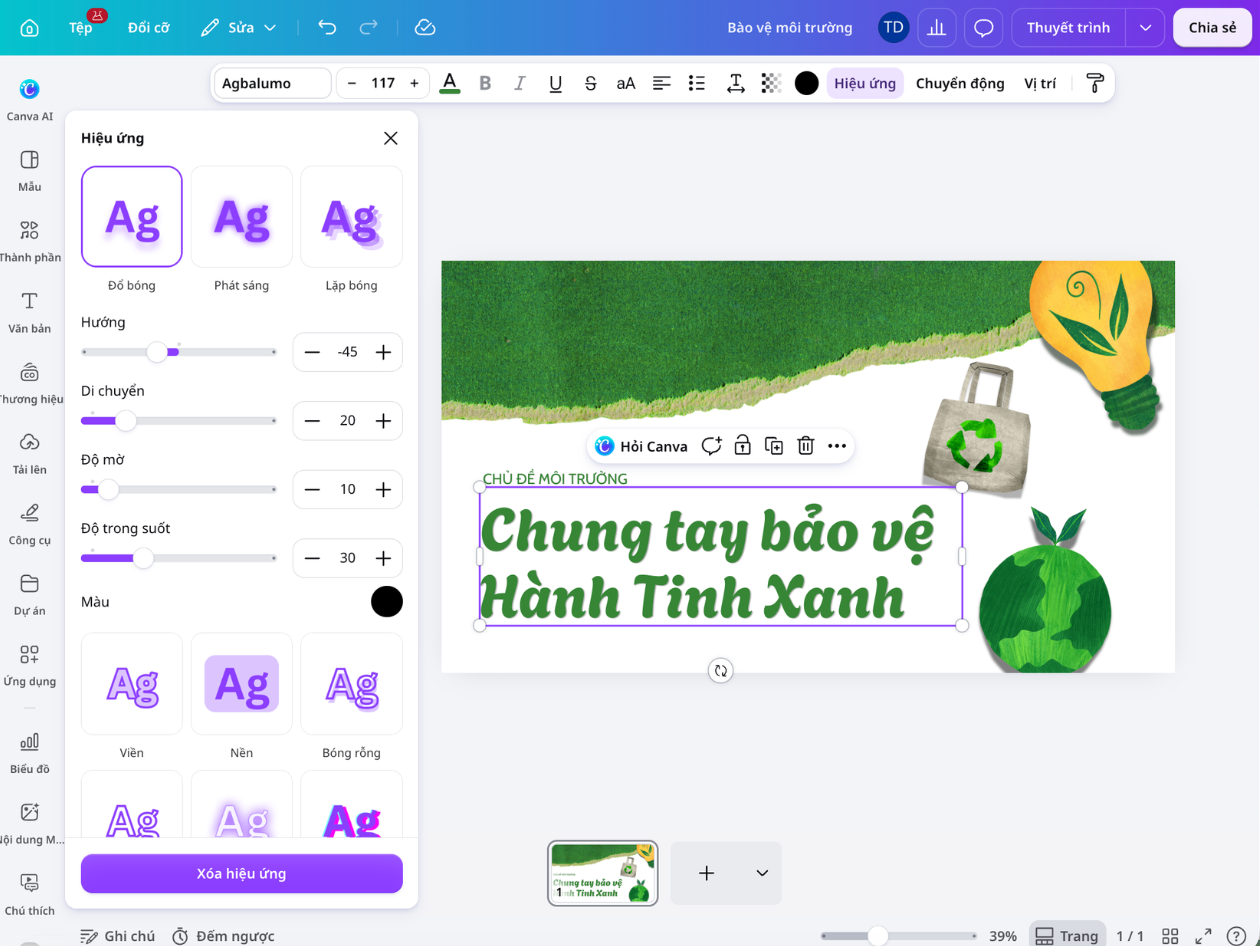
Mỗi font chữ viết tay mang một sắc thái riêng để câu chữ phù hợp hơn với cảm xúc của thiết kế. Baystar Script thanh thoát cho thiệp mời, tên riêng và câu trích dẫn, trong khi Nordminne Script tạo nét cọ đậm và giàu biểu cảm.
CoalhandLuke đem lại vẻ thô mộc, gần gũi. Anaconda Wildstyle và Owltail Brush tạo chuyển động mạnh cho tiêu đề, còn Handpicked Seashells hay Spilled Ink phù hợp với những ý tưởng vui tươi, sáng tạo và ít trang trọng hơn.
Thư viện đa dạng giúp bạn bắt đầu từ tinh thần muốn truyền tải thay vì đoán theo tên font. Từ lời chúc dịu dàng đến poster cá tính, mỗi thông điệp đều có kiểu chữ phù hợp với vai trò trong bố cục. Nét đẹp riêng vẫn hiện rõ mà không làm người đọc mất tập trung.
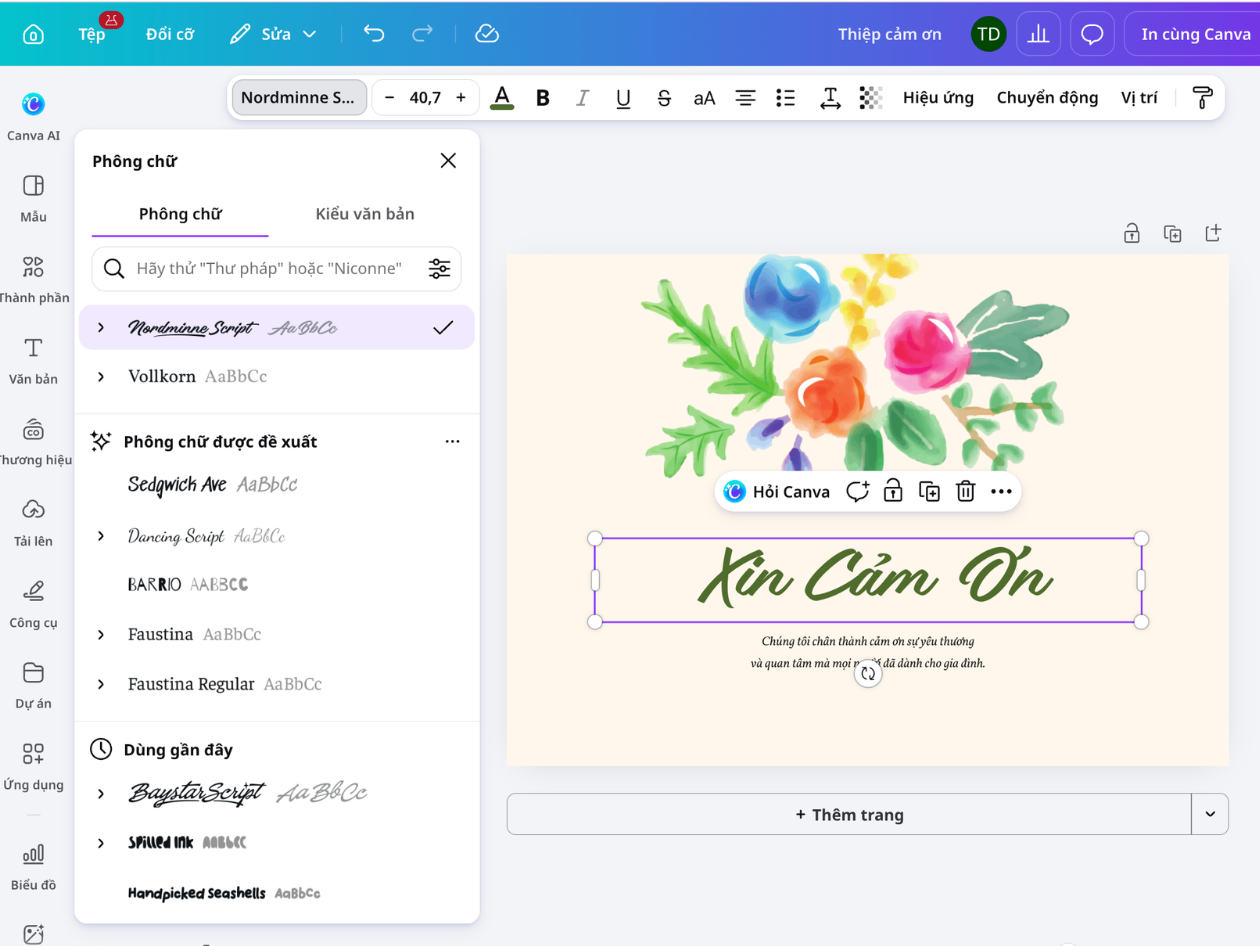
Font viết tay tiếng Việt cần thể hiện trọn dấu để cảm xúc không bị gián đoạn bởi những ký tự khó đọc. Các lựa chọn hỗ trợ tiếng Việt giúp tên riêng, lời chúc và tiêu đề giữ được hình dáng cân đối ngay cả khi nội dung có nhiều dấu.
Khả năng hiển thị được cảm nhận rõ nhất trên chính câu chữ sẽ xuất hiện trong thiết kế. Những ký tự như ă, â, ê, ô, ơ và ư cho thấy dấu có chạm nhau, quá nhỏ hoặc làm nhịp chữ trở nên nặng nề hay không.
Khi phần chữ rõ ràng, nét viết tay mới phát huy được sự mềm mại và gần gũi vốn có. Bạn dễ chọn kiểu chữ vừa truyền đúng cảm xúc, vừa bảo đảm người xem nắm bắt thông điệp mà không phải đọc lại.
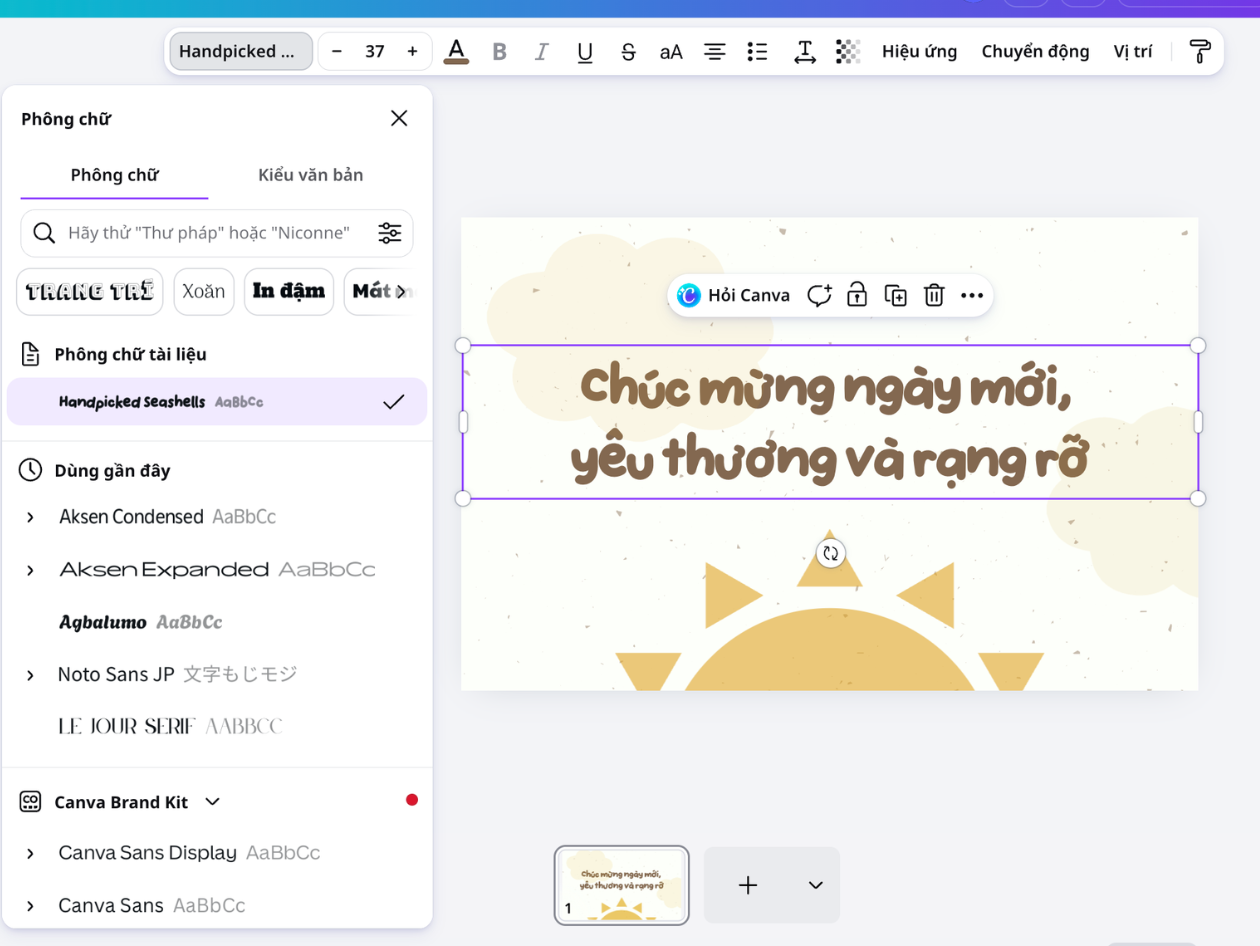
Một font đẹp trong bảng mẫu có thể tạo cảm giác hoàn toàn khác khi đặt cạnh ảnh, màu nền và khoảng trống. Canva cho phép xem kiểu chữ ngay trên hộp văn bản đang dùng, để từng lựa chọn được đánh giá trong đúng bố cục.
Chiều rộng tiêu đề, cách xuống dòng và độ tương phản trở nên rõ ràng khi câu chữ xuất hiện ở kích thước thật. Nhiều phương án có thể được so sánh để tìm ra kiểu vừa có chất viết tay, vừa giữ được trọng tâm thị giác.
Khả năng thử trực tiếp giúp quyết định về font gắn với toàn bộ thiết kế thay vì chỉ dựa vào sở thích riêng. Phần chữ vì thế hòa với hình ảnh tốt hơn và dẫn mắt tự nhiên hơn đến thông điệp quan trọng.
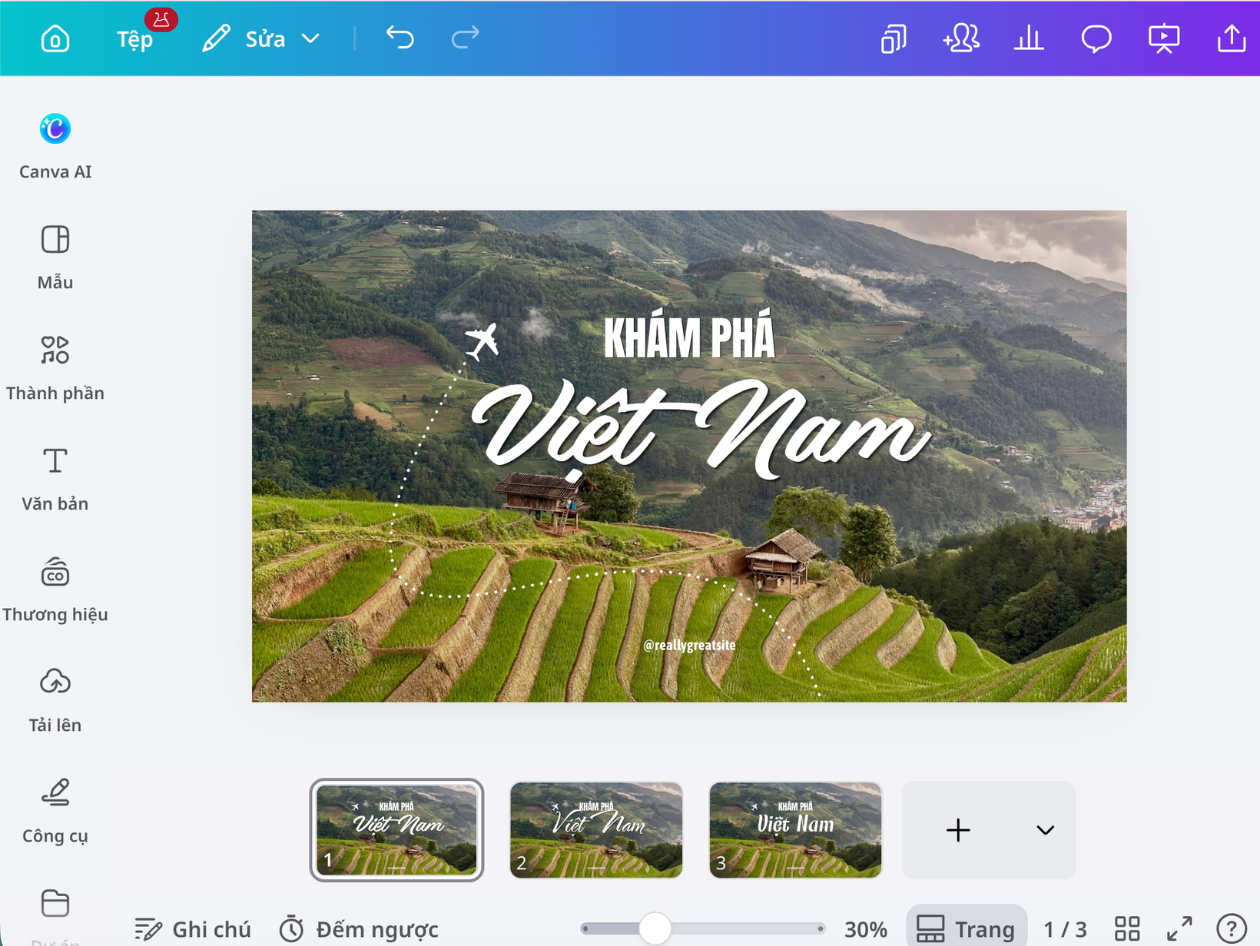
Sau khi chọn font, các tùy chọn về cỡ chữ, màu sắc, căn lề, khoảng cách và hiệu ứng giúp nét viết tay thể hiện đúng cá tính. Tiêu đề có thể nổi bật hơn mà vẫn giữ được độ rõ cần thiết trên màn hình hoặc bản in.
Với phần thông tin dài, font viết tay phù hợp nhất khi được dùng như một điểm nhấn. Một kiểu chữ đơn giản hơn cho nội dung bổ sung tạo sự cân bằng, giúp thiết kế có cảm xúc mà người xem vẫn đọc nhanh.
Việc tinh chỉnh trong bố cục thật cho thấy nét có quá mảnh, dấu có quá sát hay hiệu ứng có lấn át chữ hay không. Mỗi chi tiết được cân nhắc để phong cách và khả năng đọc cùng tồn tại, thay vì phải hy sinh một trong hai.
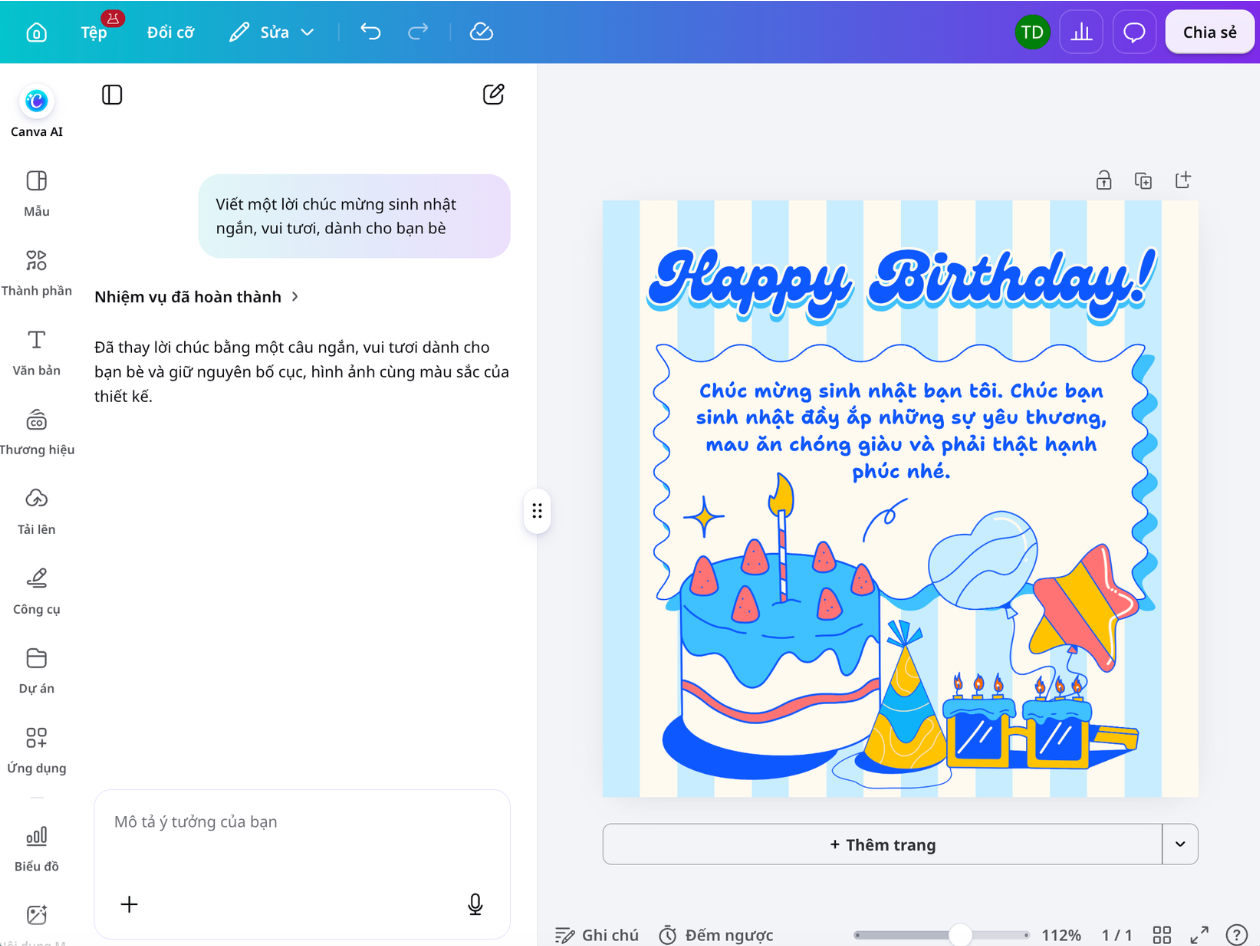
Baystar Script là lựa chọn cân bằng với nét chữ nhẹ và uyển chuyển. Nordminne Script hợp với tiêu đề cọ đậm; CoalhandLuke tạo cảm giác thủ công; Anaconda Wildstyle và Owltail Brush phù hợp với thiết kế giàu năng lượng. Nếu muốn phong cách vui tươi, hãy thử Handpicked Seashells hoặc Spilled Ink. Dù chọn font nào, hãy nhập câu có dấu tiếng Việt rồi xem trong bố cục và ở đúng cỡ sẽ dùng trước khi quyết định.
Hãy bắt đầu từ độ dài và vai trò của nội dung. Nét ký hoặc cọ giàu chuyển động thường hợp với tên riêng, tiêu đề và câu ngắn; đoạn dài nên dùng kiểu đơn giản hơn. Xem thử ở kích thước sử dụng thật, kiểm tra khoảng cách giữa chữ, dấu cùng nền phía sau rồi mới chốt.